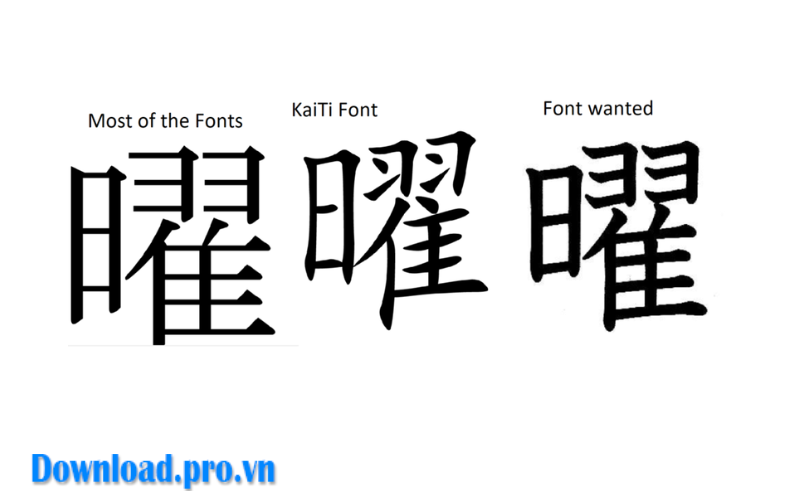
Tại sao bạn cần một bộ font chữ tiếng Trung Quốc full và chuẩn kỹ thuật?
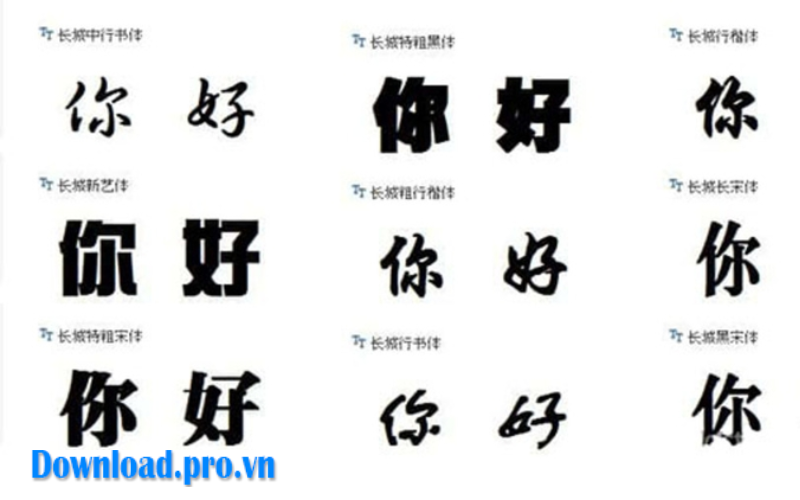
Hiện nay, tiếng Trung là loại ngôn ngữ có cấu trúc ký tự phức tạp. Nếu không sử dụng đúng bộ font chuẩn, sản phẩm cuối cùng rất dễ bị phá vỡ cấu trúc hoặc không hiển thị được nội dung.
Sự khác biệt giữa font hệ thống và font thiết kế
| Tiêu chí so sánh | Font hệ thống | Font thiết kế chuyên dụng |
| Mục đích chính | Phục vụ nhu cầu đọc văn bản cơ bản trên Windows/macOS. | Tối ưu cho đồ họa, nghệ thuật và nhận diện thương hiệu. |
| Tính thẩm mỹ | Đơn giản, trung tính, đôi khi gây cảm giác khô khan. | Đa dạng phong cách (thư pháp, hắc thể…), giàu tính nghệ thuật. |
| Độ đa dạng (Weight) | Hạn chế về độ dày, mỏng của nét chữ. | Rất đa dạng về độ dày (từ Thin đến Black), dễ dàng tùy chỉnh. |
| Đường nét chữ | Nét chữ đều nhau, thiếu sự đột phá về hình thái. | Đường nét thanh đậm rõ ràng, mô phỏng chân thực nét bút. |
| Khả năng truyền tải | Chỉ dừng lại ở mức hiển thị thông tin. | Truyền tải linh hồn tác phẩm (mạnh mẽ, uyển chuyển, cổ điển…). |
Lợi ích khi sở hữu kho font chuẩn
Dưới đây là một số lợi ích khi người dùng sở hữu kho font chuẩn:
- Tránh lỗi hiển thị: Loại bỏ hoàn toàn tình trạng lỗi font (missing glyphs) hay các ký tự biến thành ô vuông vô nghĩa.
- Tăng tính thẩm mỹ: Đa dạng hóa phong cách từ cổ điển đến hiện đại, phù hợp với mọi loại dự án từ biên tập video, làm slide thuyết trình đến thiết kế banner.
Tư duy chọn font
Khi chọn font, cần chú ý đến mục đích sử dụng. Văn bản hành chính cần sự nghiêm túc, rõ ràng; trong khi đó, các ấn phẩm truyền thông lại cần sự đột phá, bay bổng. Một chuyên gia luôn biết cách cân bằng giữa khả năng đọc (readability) và tính nghệ thuật của bộ chữ.
Top những bộ font chữ tiếng Trung đẹp online
Dưới đây là những nhóm font được phân loại theo phong cách để người dùng dễ dàng lựa chọn theo nhu cầu:
Nhóm font tối giản (Sans Serif)
Đây là nhóm font “Hắc thể” (Heiti), không có chân ở các đầu nét, mang lại cảm giác hiện đại, sạch sẽ.
- Ứng dụng: Thường dùng cho tiêu đề ứng dụng (UI/UX), phụ đề video (subtitle) hoặc nội dung trên trang web.
- Đặc điểm: Độ tương phản thấp, cực kỳ dễ đọc ngay cả ở kích thước nhỏ.
Nhóm font thư pháp và nghệ thuật
Nếu đang tìm kiếm font chữ tiếng trung đẹp online để làm bìa sách, poster phim hoặc thiết kế logo theo phong cách cổ trang, đây chính là lựa chọn hàng đầu.
- Phong cách: Thảo thư, Hành thư với những đường nét mô phỏng bút lông mực tàu.
- Cảm xúc: Mang lại hơi thở truyền thống, uy quyền và đầy tính nghệ thuật.
Nhóm font có chân (Serif) chuẩn mực
Dòng font “Tống thể” (Songti) hoặc “Minh thể” là tiêu chuẩn trong in ấn văn bản dài.
- Ưu điểm: Các nét gạch ngang mảnh và nét đứng dày giúp mắt người đọc ít bị mỏi.
- Phù hợp: Soạn thảo tài liệu học tập, dàn trang sách báo.